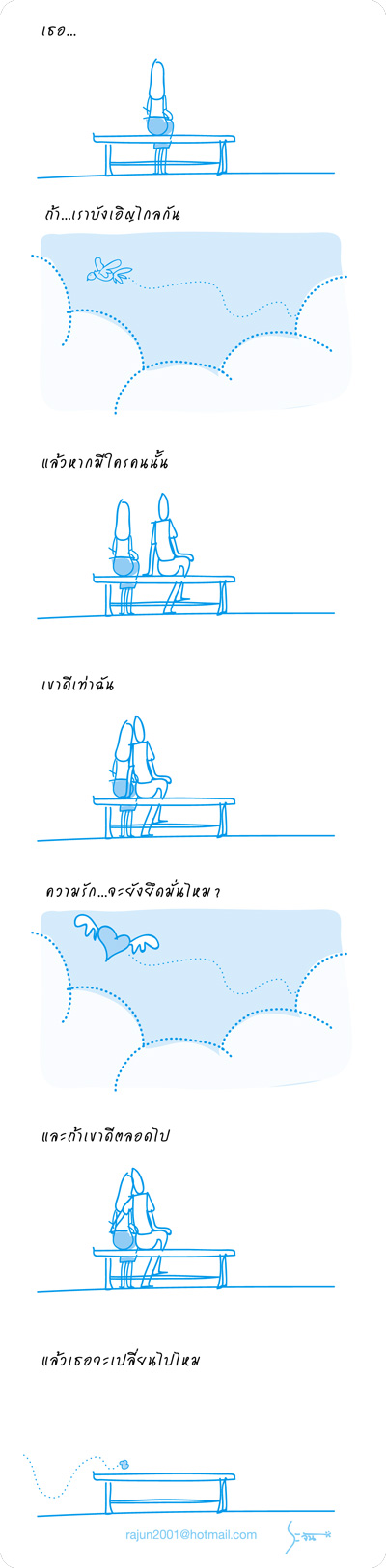
ไปเจอ [ฟอนต์ iannnnn] มา
ฟอนต์ ใครไม่รู้ สวย สะบัด เลย  :35:
ชอบผลงานชุดนี้ครับพี่ระจัน อ่านแล้วช่วยเตือนใจให้ไม่ยึดมั่นถือมั่นในความรัก เพราะมันเป็นสิ่งไม่เที่ยงแท้ ฟอนต์ที่ใช้ก็เข้ากันดี :02a:
ึคาดว่าเป็น font iannnnnJPG
ฟอนต์ ใครไม่รู้ สวย สะบัด เลย  :35:
รู้สึกพักนี้เห็นfont พี่แอน บ่อยๆ
ฟอนต์พี่แอนอีกแล้วขะรับ  :12: :22: :45:
:39: ฟอนต์ .............. พี่แอน